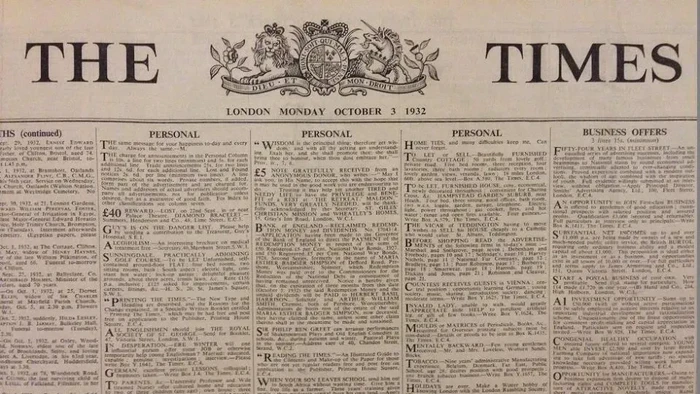
Detikers pasti sudah tidak asing lagi dengan font Times New Roman yang sering ditemui di Microsoft Office atau software lain, seperti Adobe Family hingga di Capcut pun juga ada. Tapi kalian penasaran tidak sih, kira-kira bagaimana ya sejarah dari font ini?
Mungkin kalian akan sedikit terkejut bila mengetahui bagaimana awal mula sejarah Times New Roman terukir. Berangkat dari sebuah kritikan, hingga akhirnya huruf klasik ini menjadi begitu populer seperti sekarang.
Mari berwisata ke masa lalu, tepatnya tahun 1930-an, di mana pertama kalinya Times New Roman muncul ke publik. Debutnya di surat kabar London bernama The Times, yang mana merupakan tempat font ini dirancang.
Seorang penasihat tipografi dari Monotype Corporation, Stanley Morison, menilai kalau font yang digunakan oleh The Times terlalu jadul. Menurutnya, surat kabar ini tidak mengikuti tren tipografi modern.
Tidak marah ataupun sakit hati, The Times justru menerima kritikan tersebut dan meminta Morison untuk membuat font baru yang lebih baik dari yang mereka gunakan saat itu. Di 1931 proyek dimulai, dan Morison menggandeng seorang juru gambar bernama Victor Lardent.
Keduanya mulai membuat konsep dengan fokus pada dua hal, yakni terkait efisiensi dan keterbacaan. Efisiensi di sini maksudnya bagaimana memaksimalkan jumlah huruf yang dapat dimuat dalam satu baris dalam satu halaman.
Dalam hal ini, Morison sangat tegas. Ia ingin setiap percetakan yang menggunakan hurufnya menjadi ekonomis. Namun di sisi lain dirinya tidak ingin mengesampingkan fungsi dari hurufnya, sehingga tetap nyaman saat dilihat dan dibaca.
Morison pun mencari inspirasi dari desain huruf klasik. Dirinya menyukai tampilan Plantin modern, yang didasarkan pada huruf Gros Cicero lama buatan Robert Granjon.
Untuk mencapai efisiensi seperti yang diinginkannya, Morison mengatur tinggi dari huruf-huruf tersebut. Jarak antara bagian atas dan bawah huruf kecil yang tidak memiliki lebihan garis ke atas atau ke bawah disesuaikan. Maksudnya di sini huruf tanpa lebihan garis itu seperti a, c, m, n, x, dan lainnya.
Dirinya turut mengurangi tracking atau jarak antara satu huruf ke huruf lainnya. Jadi Morison berusaha membuat jenis huruf yang lebih padat.
Mungkin setiap orang akan berpikir, huruf yang berdekatan akan membuatnya sulit untuk dibaca. Nah untuk mempertahankan tujuan keduanya yaitu keterbacaan, Morison mengubah bentuknya.
Bagian yang lebih tebal dari setiap huruf (misalnya garis vertikal di bagian atas huruf 'n') diperlebar. Dengan begitu huruf-huruf serupa akan menampung lebih banyak tinta dan tampak lebih gelap ketika dicetak, yang mana kontrasnya lebih jelas di atas kertas. Lalu setiap goresan yang ada di ujung huruf dibuat lebih tipis. Hal tersebut menjaga bentuk huruf agar tampak lebih baik, tampilan lebih bulat, dan mudah dibaca.
Pada 3 Oktober 1932, The Times meluncurkan jenis huruf barunya ini. Itu pertama kalinya sebuah surat kabar mendesain jenis hurufnya sendiri dan mereka memiliki hak eksklusif selama setahun, dihimpun detikINET dari nypl, Rabu (11/6/2025).
The Times menggunakan Times New Roman asli selama 40 tahun. Surat kabar ini kemudian berganti jenis huruf sebanyak lima kali antara 1972 dan 2007.